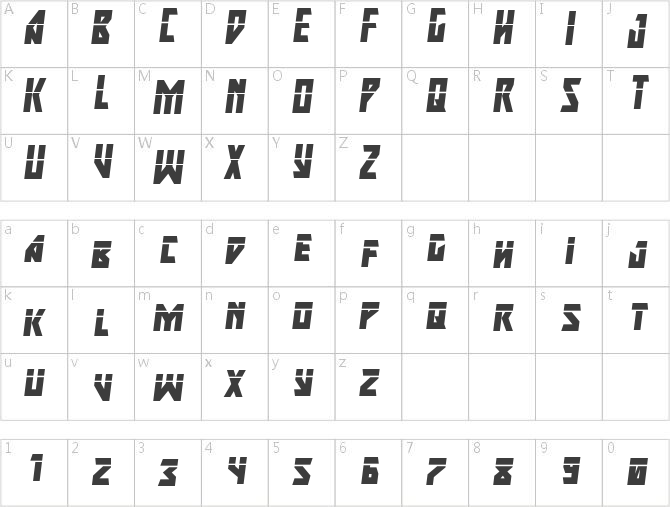
Major Force Laser Italic 詳情頁(yè)
Major Force Laser Italic
Major Force Laser Italic字體字庫(kù)是一款讓人賞心悅目、百看不厭的英文字體,適合各類(lèi)廣告和產(chǎn)品包裝設(shè)計(jì)應(yīng)用,字體大小0.02MB,格式為ttf字體,上傳用戶(hù)是趙家玉,作者/版權(quán)方為未知